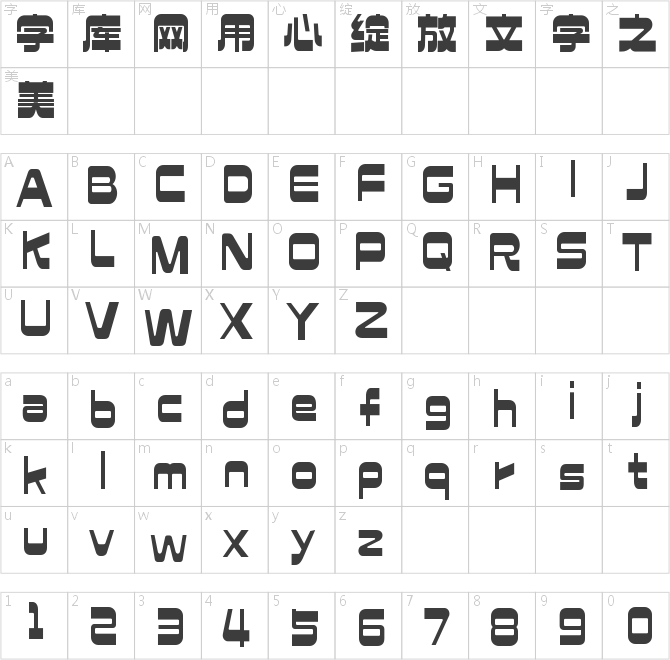
造字工房超凡體 詳情頁
字體名稱: 造字工房超凡體
造字工房超凡體
造字工房超凡體介紹
造字工房超凡體字體字庫是一款讓人賞心悅目、百看不厭的中文字體,適合各類廣告和產(chǎn)品包裝設(shè)計(jì)應(yīng)用,字體大小3.53MB,格式為ttf字體,上傳用戶是晴朗,作者/版權(quán)方為造字工房
造字工房超凡體效果圖